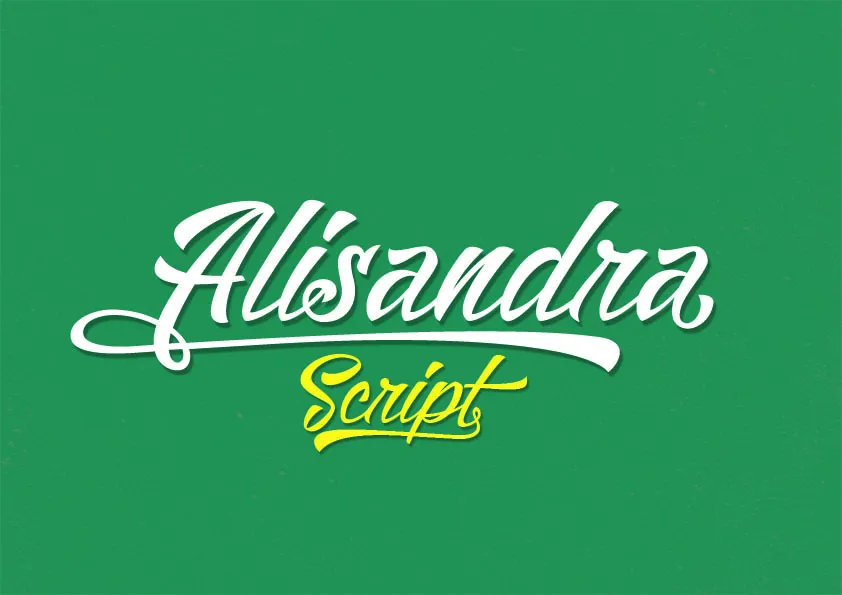
A fonte “Alisandra” é uma criação elegante e sofisticada projetada para escrita a mão. Ela é ideal para qualquer design que exija um toque delicado e artesanal, como letras de arte ou desenhos de livros antigos. Criada pelo designer Hamilton, essa fonte oferece uma variedade rica de estilos, incluindo linhas elegantes e traços acentuados que permitem ao usuário criar texturas diferentes dependendo da aplicação. Compreender o conceito de “calligraphy” é fundamental para apreciar a capacidade desta fonte. Ela é perfeita para trabalhos que exigem uma escrita a mão com estilo, desde cartões personalizados até artigos literários ou históricos. Sua estrutura minuciosa e precisão permitem aos criadores de design alcançar um nível refinado em seus projetos. Hamilton trabalhou arduamente na construção desta fonte, garantindo que ela atenda às necessidades de quem busca uma escrita a mão perfeita para seus trabalhos. Se você está procurando por algo mais do que simplesmente textos tipográficos, então “Alisandra” é certamente o caminho para encontrar esse design único e incrivelmente detalhado.